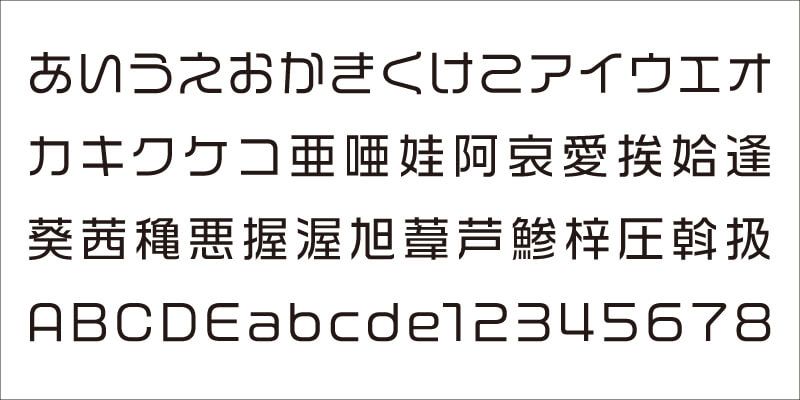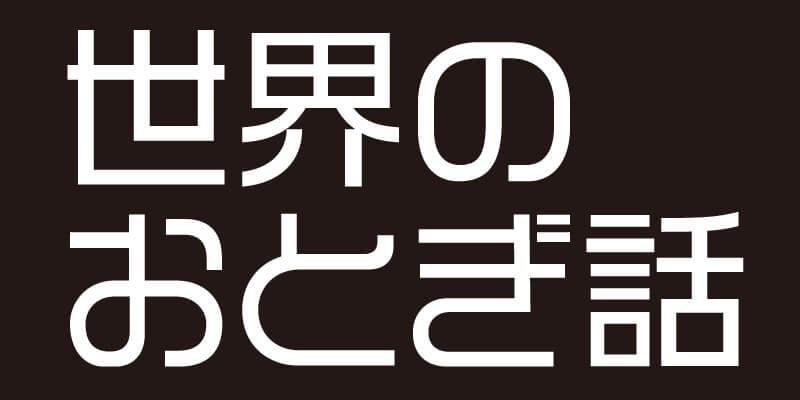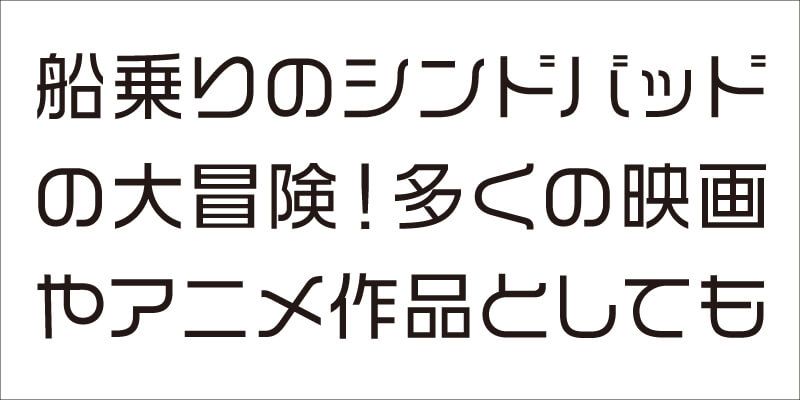
Die chinesischen ideografischen Zeichen von VDL-LogoJr übernehmen die großen Zwischenräume von VDL-LogoG und werden mit Kana-Silbenzeichen kombiniert, bei denen Kurven und gerade Linien schön komponiert sind und einen guten Sinn für Modernität haben. VDL-LogoJr ist ein sehr „grafisches“ Schriftdesign. Wie ein frecher Junge hat VDL-LogoJr einen einzigartigen, schelmischen und freundlichen Charakter.